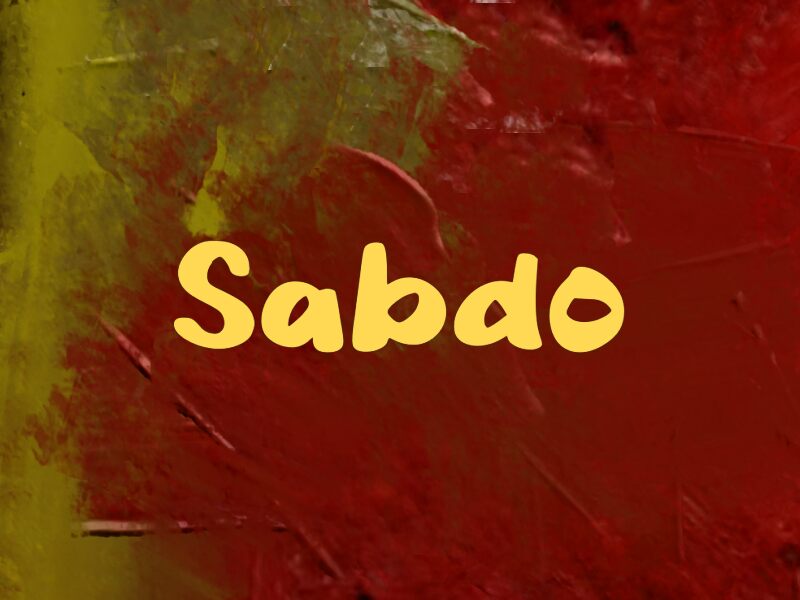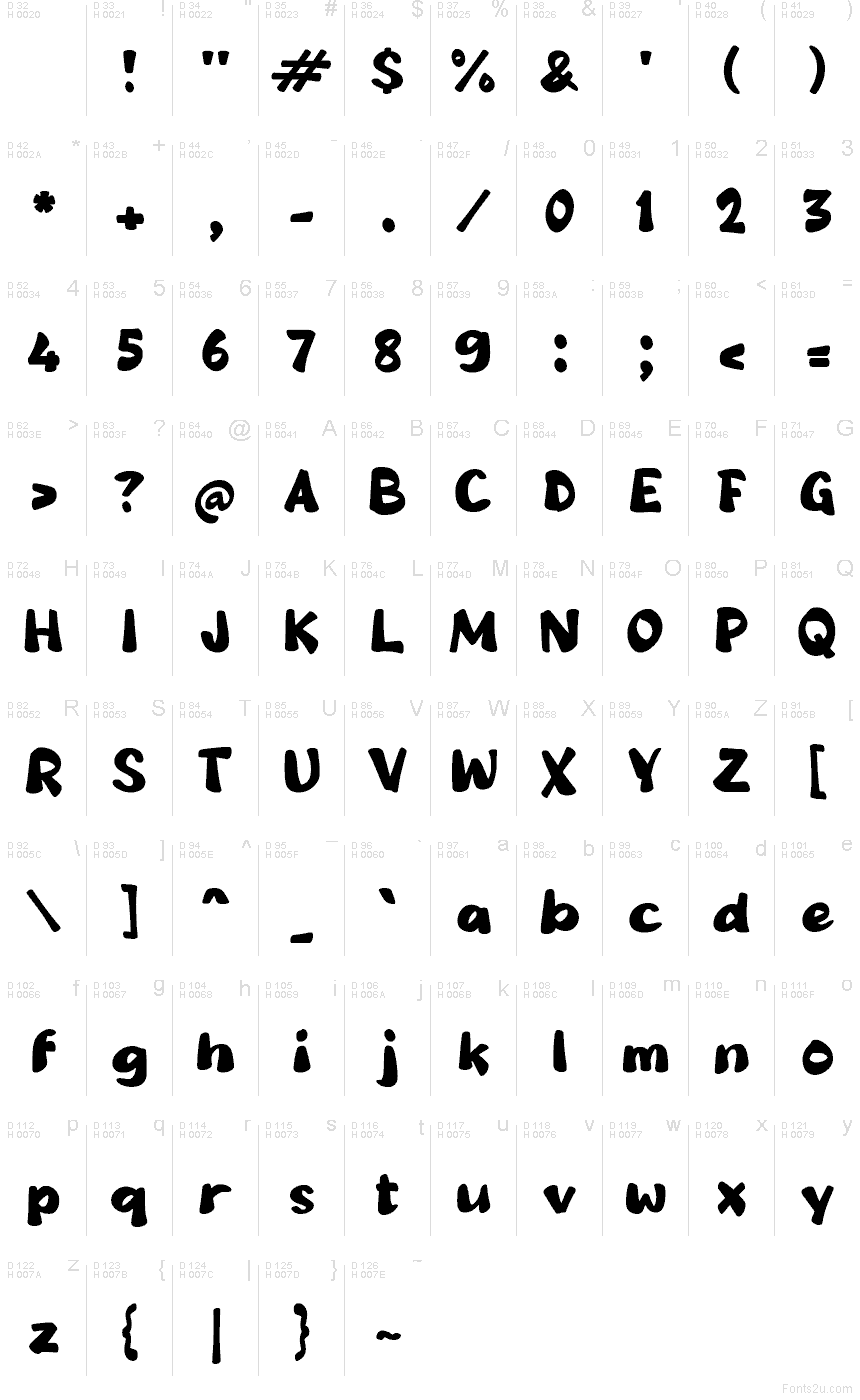
Sabdo 字体
Sabdo 由 Wep 设计,是一款免费的笔刷字体。它由宽阔且圆润的笔触构成,赋予了字符一种圆滚滚、如同剪纸般的轮廓。柔和的曲线和略显不规则的手写节奏,让设计摆脱了生硬的刻板感,呈现出一种手绘招牌的自然韵味,而非普通的马克笔字迹。
这种扎实且亲切的造型非常适合咖啡馆菜单、零食包装、儿童活动海报、YouTube 封面图以及随性的品牌设计,能为简短的文字增添一抹温馨的图形张力。它也非常适合用于贴纸和社交媒体标题,尤其是当你需要大而简洁的形状,且无需额外装饰就能保持高表现力时。